Pues bien, seguimos y el nivel no baja, porque hoy traemos a Lettering Time y para todos vosotros a uno de los reyes de las letra en gran formato Ben Johnston.
Se que pocas presentaciones hacen falta para Ben ya que muchos de vosotros seguĂs y adoráis su trabajo desde hace años, asi que sin mas pasemos a charlar con Ben Johnston.
Los murales tipográficos que realizas son realmente impresionantes, pero ... ¿cĂłmo se llevan a cabo estos grandes murales? Se comienza con el diseño en papel y en formato pequeño o directamente a gran formato? Por favor, cuĂ©ntanos el proceso que sigues para hacer uno de tus maravillosos murales de gran tamaño.
Empiezo la mayorĂa de los trabajos con un boceto en papel hasta que defino el concepto. A partir de ahĂ mido el espacio y veo cĂłmo la pieza va a encajar y luego hago los ajustes en mi diseño. Entonces pasĂł todo el diseño al ordenador y juego con el diseño hasta que estoy contento con Ă©l. A partir de ahĂ es el momento de pintar a gran escala.
El proceso de pintura puede durar desde unas horas hasta un par de semanas, dependiendo de la complejidad y de qué medio estoy usando.
Al mostrar su trabajo en el blogs y las redes sociales de Lettering Time, muchos seguidores nos preguntan sobre que tipos de materiales (pinceles, marcadores y pinturas) utilizas para tus murales, podrĂa aclarar esta cuestiĂłn.
Realmente todo depende del tipo de superficie en la que estoy trabajando. Si estamos trabajando en una pared lisa de interior, funcionan bien rotuladores de graffiti, si por el contrario se trata de una pared más rugosa suelo pintar la superficie y luego trabajo con un pincel para diseños mas simples.
Yo tambiĂ©n me dedico profesionalmente al lettering, caligrafĂa y tipografĂa, pero uno de los aspectos que veo más difĂcil en la realizaciĂłn de grandes murales es mantener un adecuado diseño de las formas de cada una de las letra y el espaciamiento entre ellas, ¿CĂłmo consigue esto y que dificultades encuentras en el diseño de estos grandes murales?
Creo que lo más importante es ver cĂłmo el diseño va a vivir y encajar en el espacio. Es necesario diseñar tambiĂ©n en torno a los elementos en el espacio, por lo que me resulta siempre de gran ayuda trabajar a travĂ©s de una fotografĂa de la pared que se va a pintar.
Hablando de los clientes, en tu cartera podemos encontrar algunos de la talla de Disney, Audi, Shell ... ¿CĂłmo llegan hasta ti estos clientes y como es trabajar con ellos?
La cartera de clientes ha crecido como una progresión natural al conseguir más experiencia y trabajando en una amplia gama de proyectos a lo largo de los años. Me gusta trabajar con gente nueva y varios clientes en la misma semana, ya que realmente ayuda a crecer como diseñador. Cuantos más trabajos realizo, mayor número de clientes me buscan para realizar trabajos con ellos.
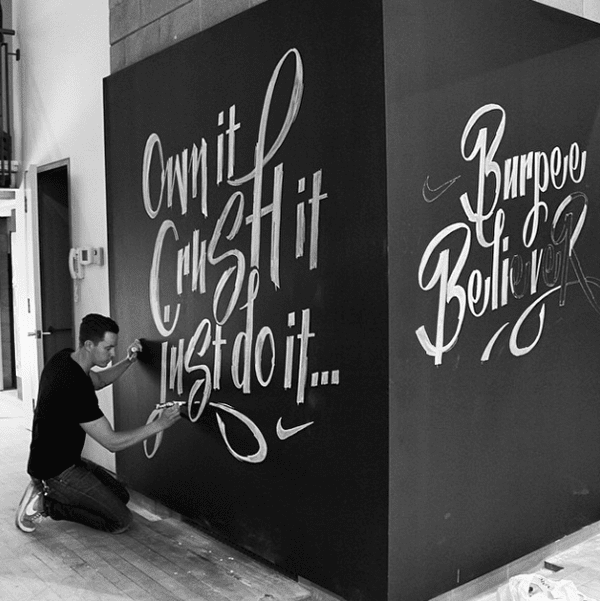
En los Ăşltimos años, parece que hay un nuevo "boom" de todo lo hecho a mano, ¿has notado esto en el aumento de los clientes que requieren de tu trabajo?
Definitivamente hay una gran tendencia en cuanto a la tipografĂa y al lettering y ha habido un aumento en los tipos de proyectos, pero me gusta tener siempre cosas frescas y probar nuevos estilos para no quedar atrapado en una rutina. Creo que la tendencia se puede ralentizar un poco en el futuro, pero siempre habrá una necesidad de letras por encargo y tipografĂa.
En tu porfolio podemos ver cĂłmo has llevado la letra a otros medios innovadores, como la impresiĂłn en 3D o el grabado a laser en madera, ¿cĂłmo fue esta experiencia y que opiniĂłn tienen los clientes sobre esto?
Como ya he dicho me gusta probar cosas nuevas constantemente y trabajar en nuevos medios ya que abre puertas y procesos que no sabĂa si serian posible. Me parece que favorece el colaborar con profesionales en diferentes campos para ayudar realmente llevar los proyectos a la realidad.
Y la pregunta obvia... ¿DĂłnde crees que vas a trabajar o que te gustarĂa hacer en el futuro?
Por el momento sólo me estoy tomando la vida con la mentalidad de realizar un solo proyecto al mismo tiempo, pero estoy seguro que con el trabajo duro, nuevas y emocionantes oportunidades surgirán, por lo que tendremos que esperar y ver lo que se viene.